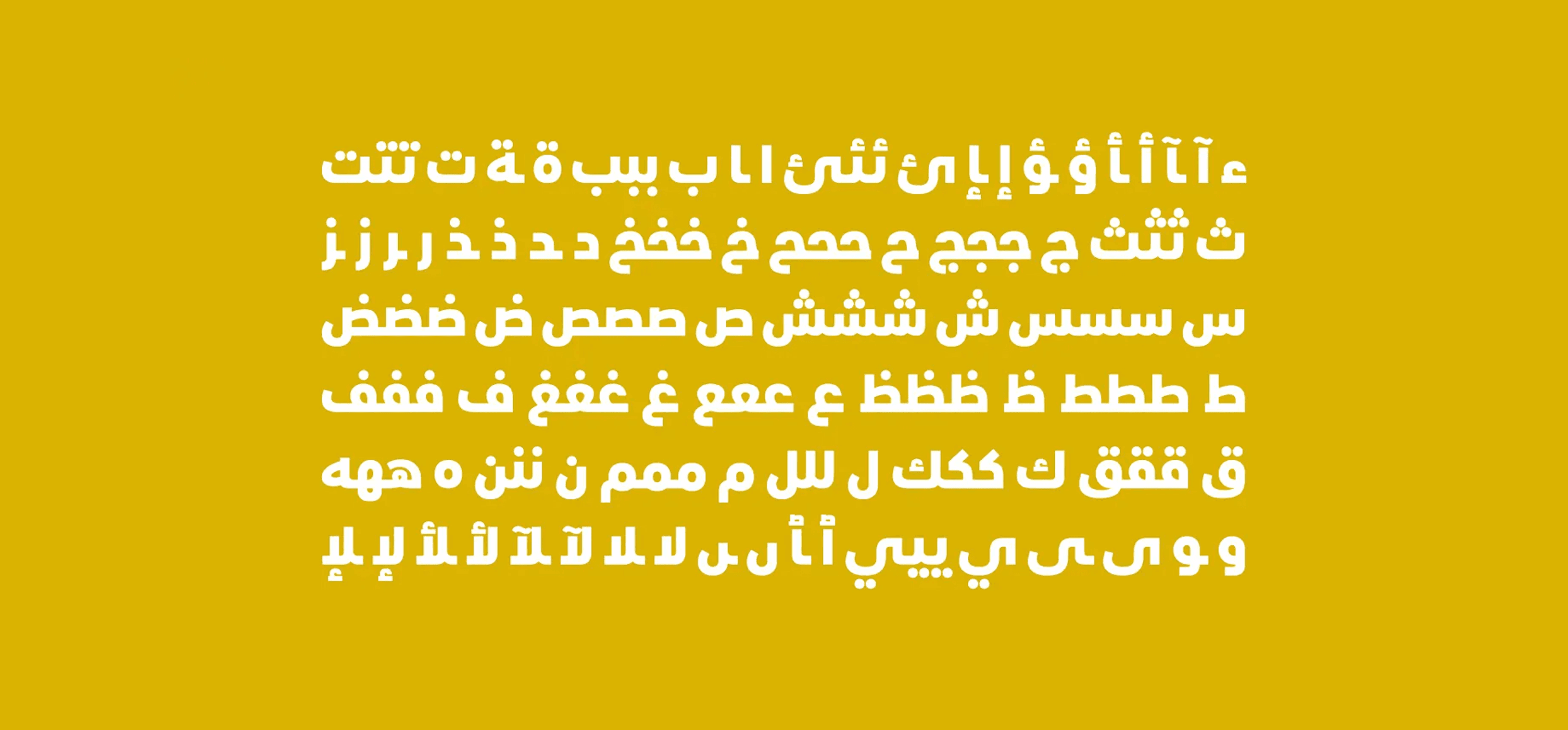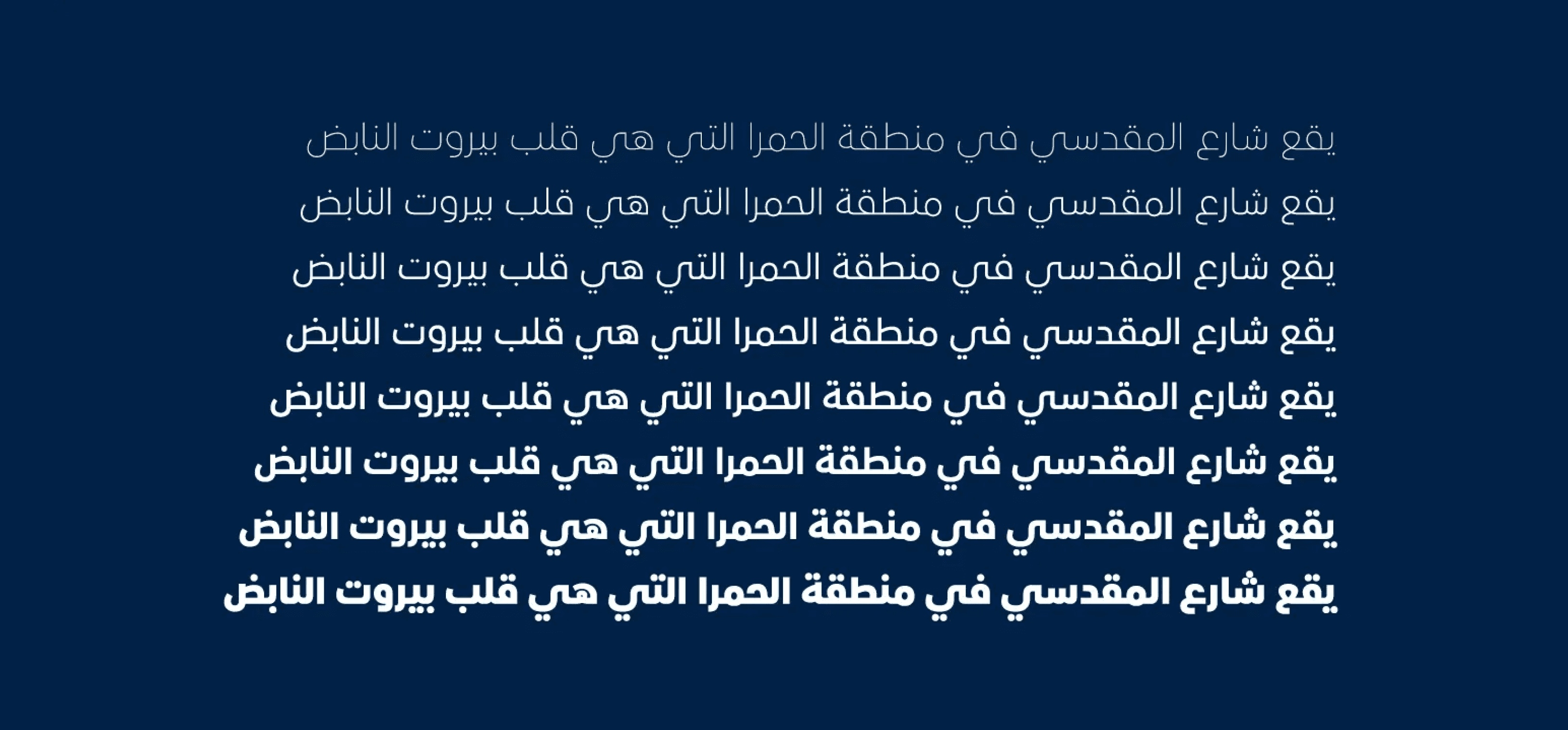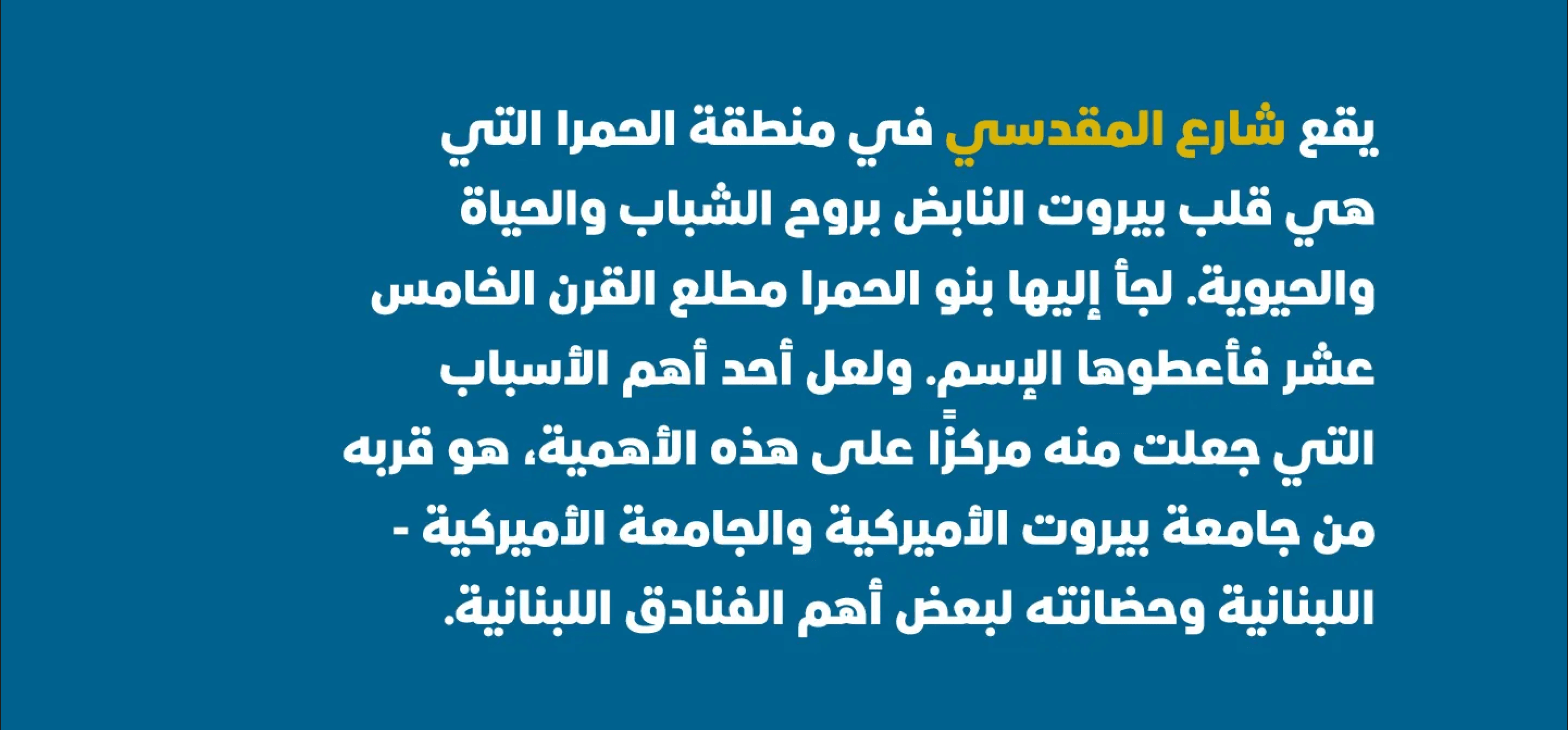
مكدّسي هو خط علامات تجارية عربي صممته نادين شاهين. تتألف العائلة من 8 أوزان تتراوح من "هيرلاين" إلى "بلاك"، وتوفر مرونة كبيرة في التصميم وفي مجموعة متنوعة من الاستخدامات. تصميمه مزيج بين النسخ والكوفي، وهو مناسب للعناوين، وواجهات المستخدم، والإعلانات، والعلامات التجارية. يتميز الطابع العام للخط بالود وسهولة الوصول، مع مظهر وإحساس عصري. يدعم الخط اللغة العربية، ويتضمن أرقامًا نسبية وجدولية. مكدّسي هو جزء من مجموعة "2020: بعد السقوط".